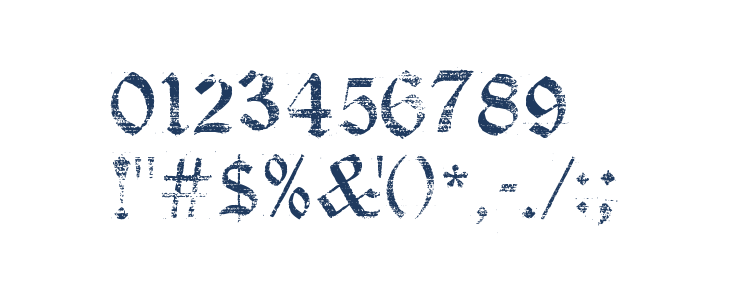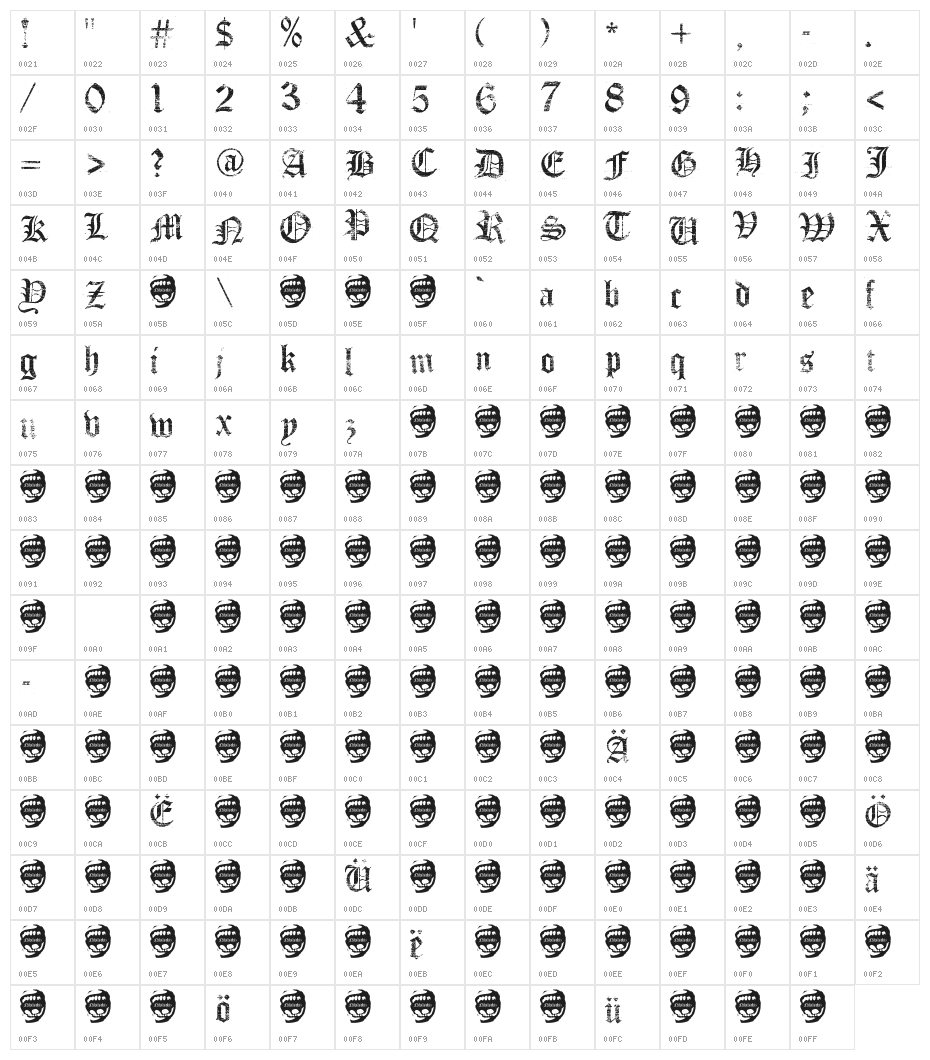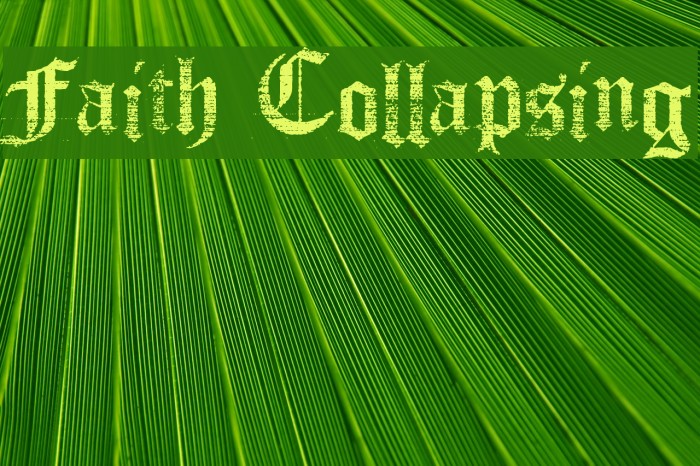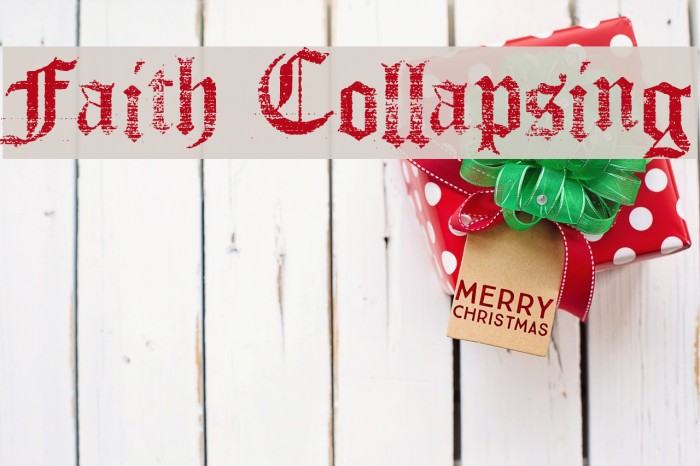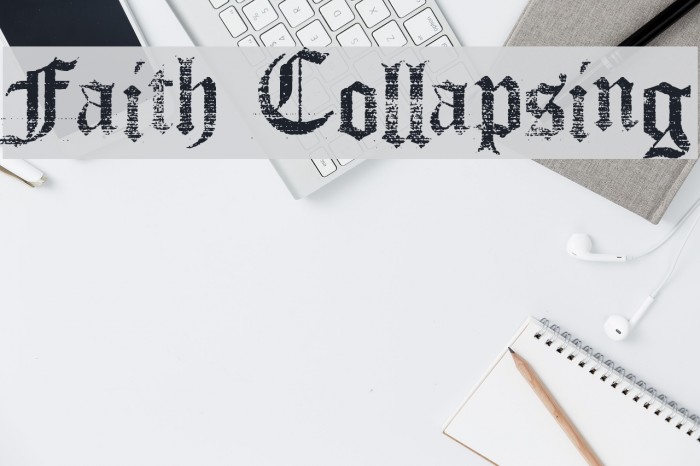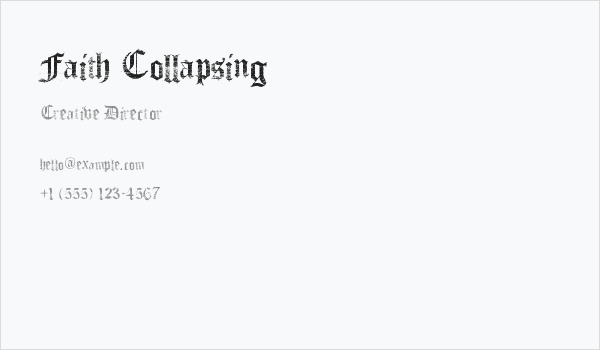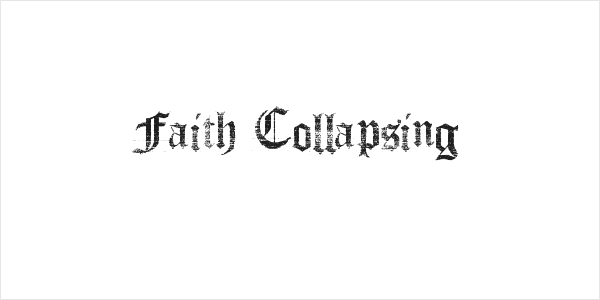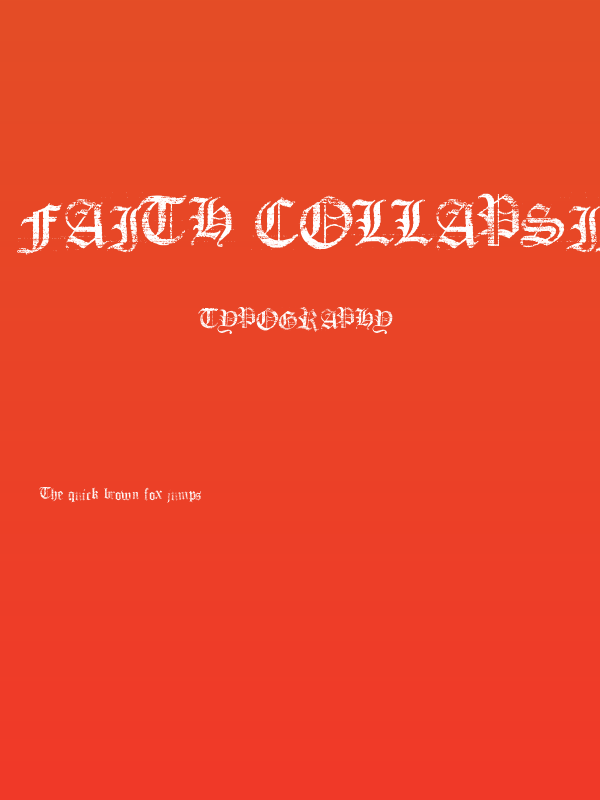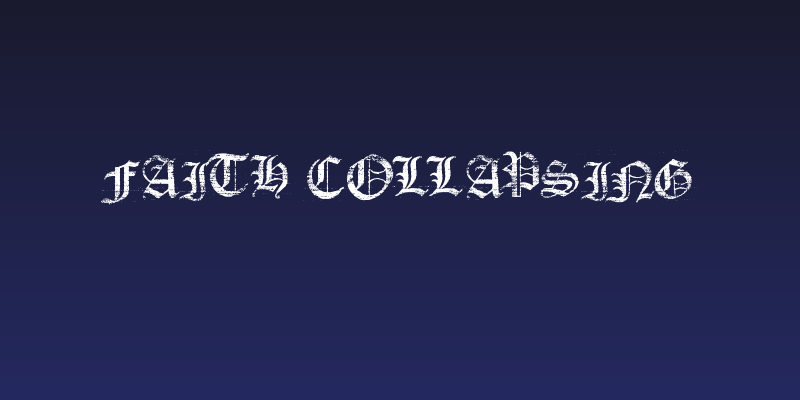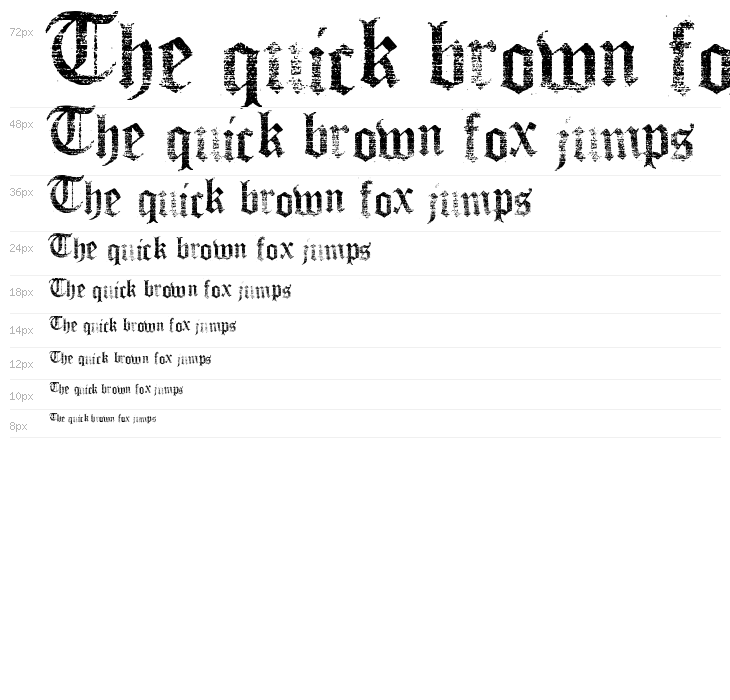
Faith Collapsing Font
| Progetti proposti | Ideal for projects requiring a historical or gothic theme, such as book covers, posters, or branding for vintage-themed events. |